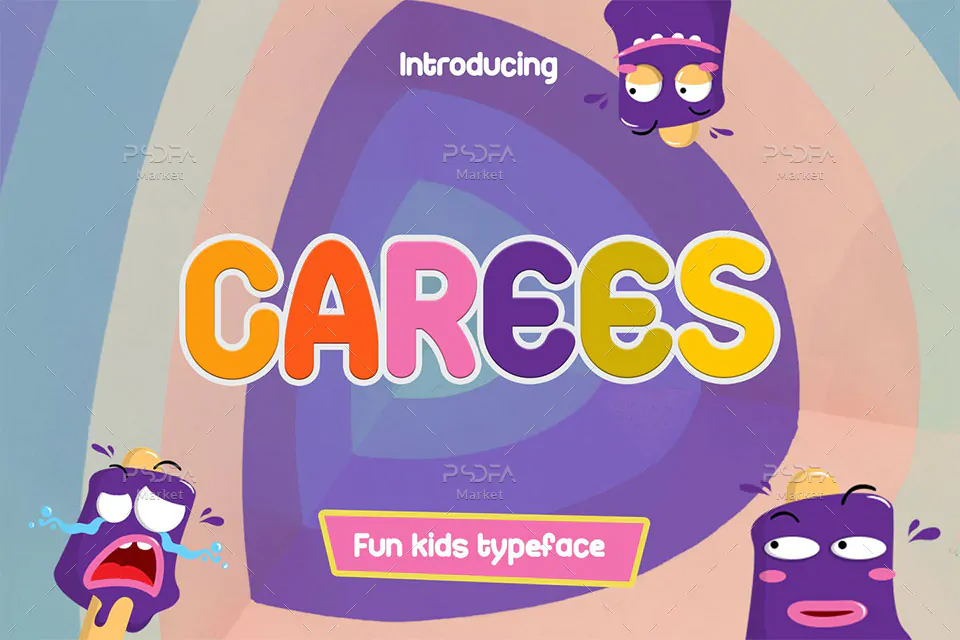
فونت کودکانه و کارتونی گیم Carees به همراه وب فونت یک قلم فوق العاده زیبای انگلیسی است که مناسب جهت استفاده در طرح و پروژههای گرافیکی مختلف به خصوص طراحی انواع تصاویر کودکانه، کارتونی و گیم میباشد. این فونت زیبا در قالب 2 فایل OTF, TTF در فایل محصول قرار دارد که با نصب یکی از این 2 فرمت در پوشه فونتهای سیستم میتوانید از این فونت انگلیسی در تمام نرم افزارهای گرافیکی و تایپ متون همچون فتوشاپ، افتر افکت، پریمیر، ورد، پاورپوینت و … استفاده کنید.
فونت فان و شاد Carees در وزن معمولی (Regular) طراحی شده است که میتوانید از آن در طراحی بسته بندی محصولات، لوازم التحریر، بگهای خرید و هدیه، ظروف یکبار مصرف، رابط گرافیکی گیم، تقویم، پوستر، بنر، بروشور، تراکت، چاپ تیشرت و دیگر طرحهای گرافیکی استفاده کنید. همانطور که ذکر شد نسخه وب فونت این قلم زیبا نیز با فرمتهای WOFF, WOFF2 در فایل محصول قرار دارد که از آنها میتوانید در طراحی صفحات وب استفاده کنید.
- نام فونت: Carees
- وزن: Regular